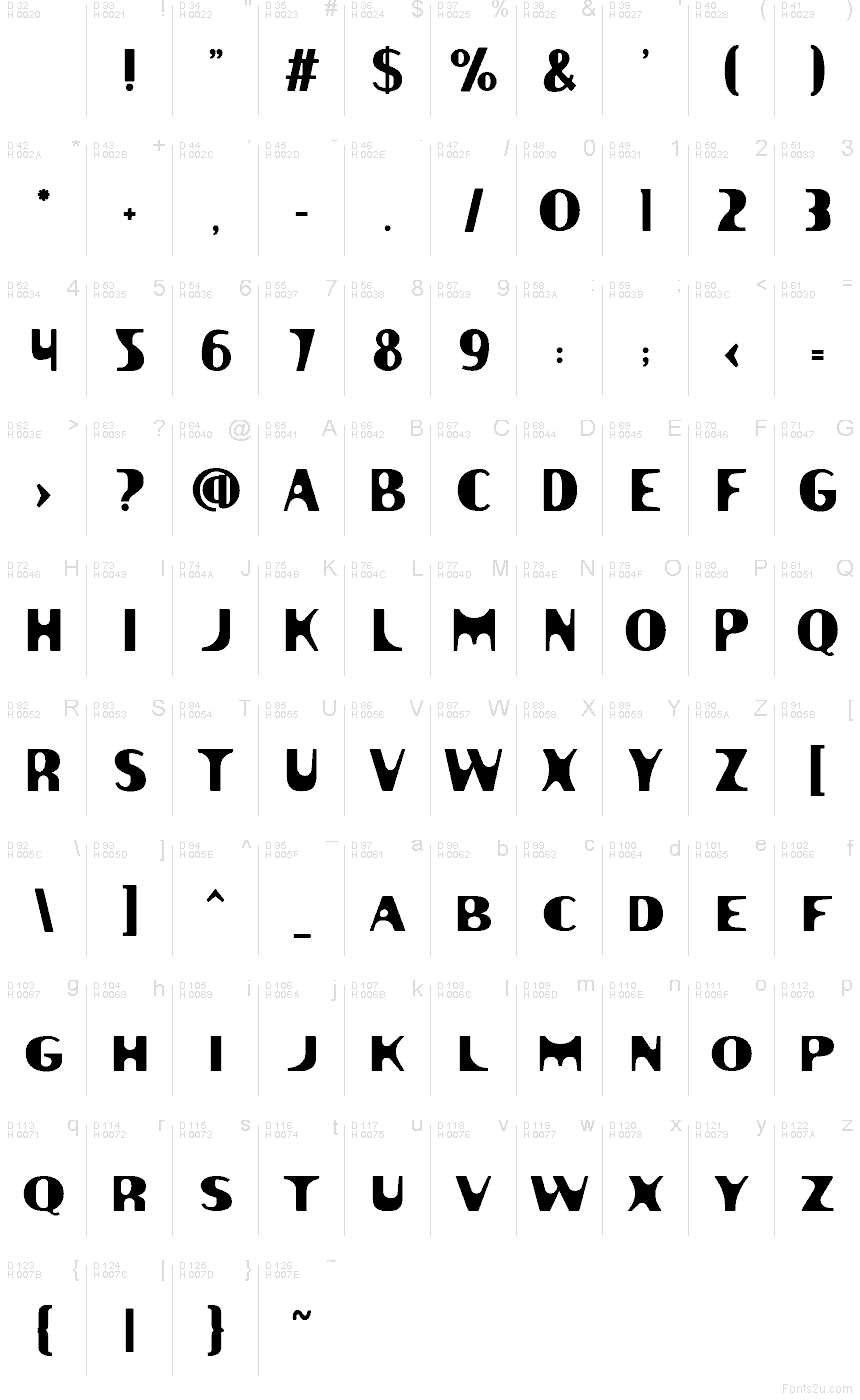
Savenir Display
Savenir Display od Putracetol Studio je bezplatné písmo typu display, ktoré definujú široké čierne tvary prerušené zaoblenými výrezmi, kruhovými zárezmi a niekoľkými štvorcovými vonkajšími rámami. Táto silueta dodáva písmenám plagátovú hutnosť, zatiaľ čo vykrojené biele priestory bránia tomu, aby písmo pôsobilo len ako prostý geometrický blok.
Design má dostatok výraznosti pre obaly albumov, módne nadpisy, plagáty k akciám, obaly produktov a krátku grafiku pre sociálne siete, kde má kompaktné slovo pôsobiť skôr graficky než neutrálne. Uzavreté tvary a tupé hrany z neho tiež robia šikovnú voľbu pre logá alebo titulky, ktoré ťažia z trocha neobvyklého rytmu pripomínajúceho papierové výstrižky, namiesto štandardného bezpätkového prístupu.